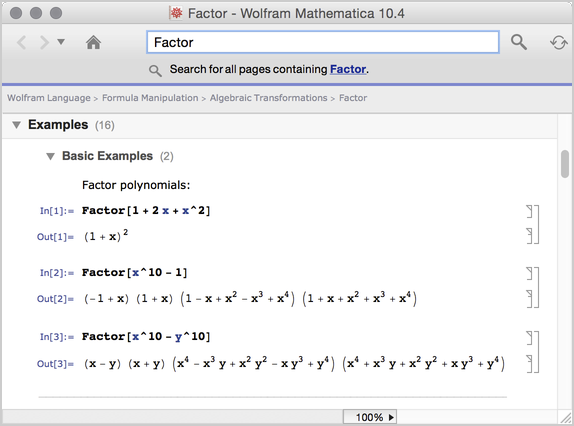
Nuevo tipo de letra para código
El nuevo tipo de letra para código es ligero, moderno, tipo sans serif, ideal para presentaciones en alta resolución.
A continuación, el tipo de letra anterior para código para comparación.